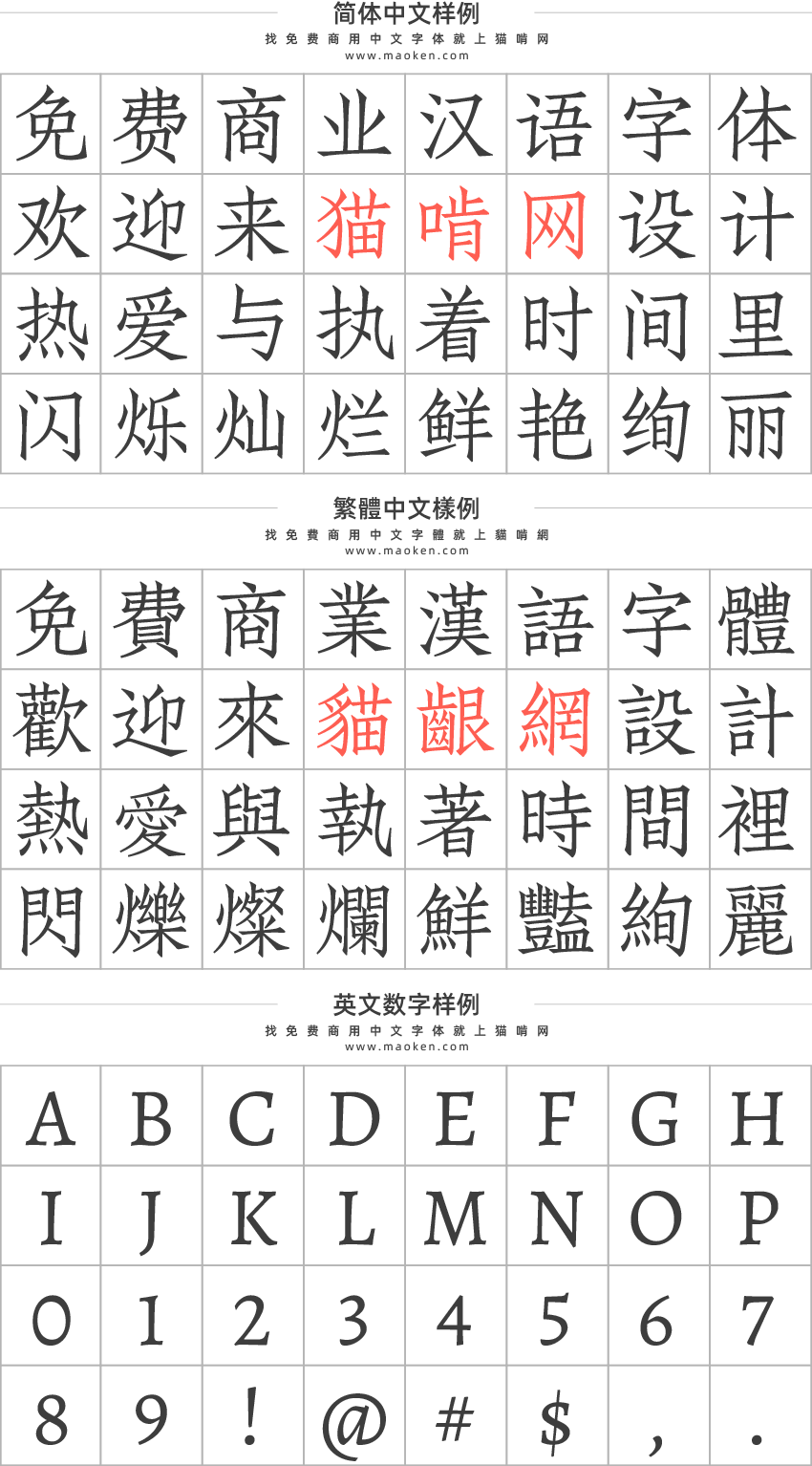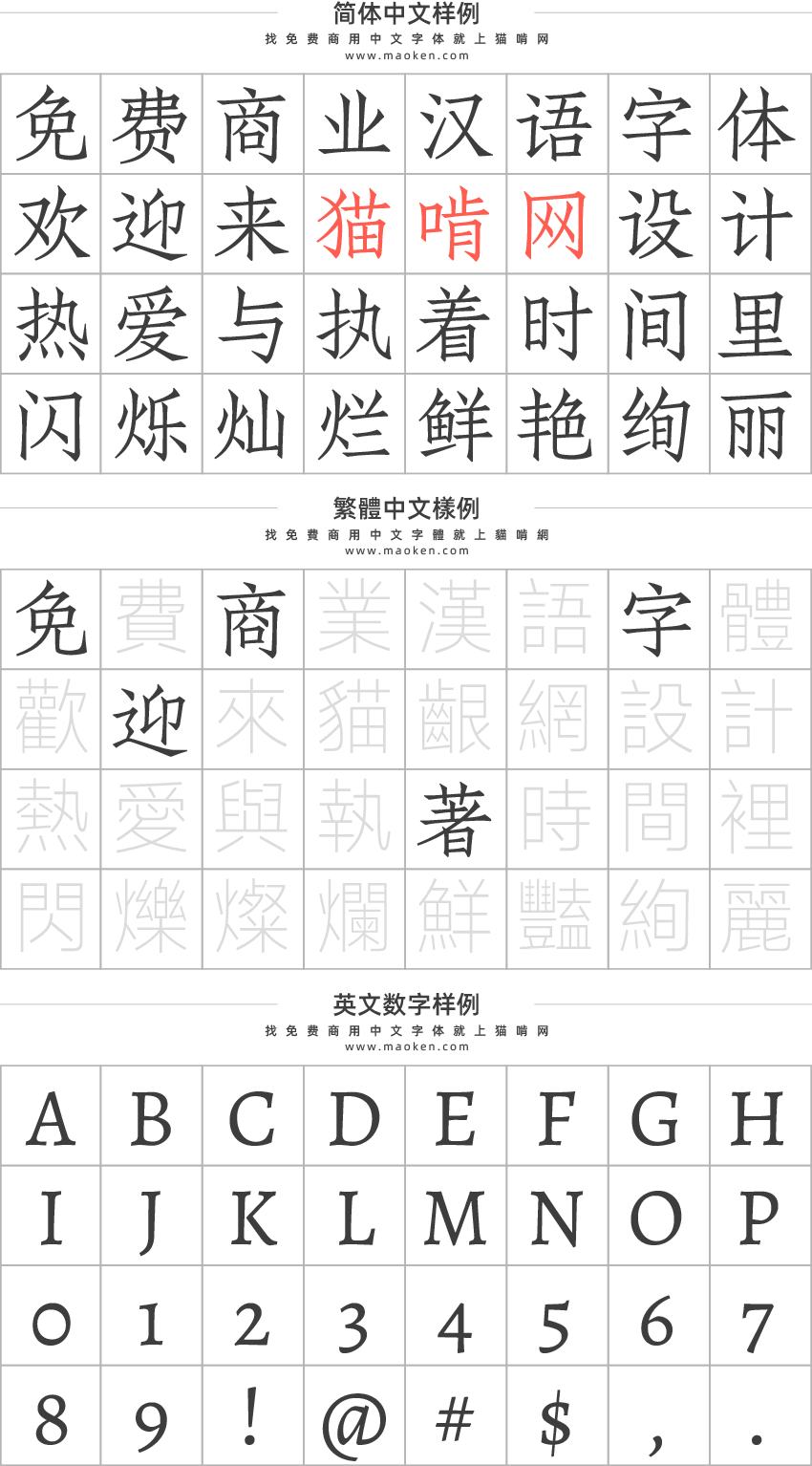
「朱雀仿宋」是璇玑造字的开源仿宋字体计划,志在最终提供高质量的、支持多语言的正文仿宋解决方案。
仿宋作为「宋黑仿楷」中文四大基础字体之一,长期缺乏开源许可证下的选择。我们希望「朱雀仿宋」可以弥补这一空缺,为开源软件与 TeX 社区贡献一份力。
上世纪初,仿宋活字一度品类繁盛,开发、应用风行一时。然而时过境迁,市面上的仿宋最终收敛于「华丰真宋」一系,这也是今天大多数人所熟悉的仿宋样貌。「朱雀仿宋」则以民国仿宋活字「南宋」为蓝本,在满足现代排印需求的前提下,尝试为正文仿宋字库带来一缕新鲜空气。
当前我们发布的「朱雀仿宋」仍为「预览测试版」,尚处于项目早期阶段;无论是设计风格还是字形、排版质量,都不代表正式版情况。因此,
「朱雀」的未来,由你定义
在开发「朱雀」的过程中,我们陷入了选择困难。于是,我们决定提早发布测试版,倾听「朱雀仿宋」的用户想要什么。我们真诚地邀请您拨冗填写此问卷:
璇玑正在尝试一种全新中文字库设计模式。得益于我们开发的最新技术,璇玑的设计师可以直接将人工智能作为设计工具去使用,我们也因此能以迭代的方式开发「朱雀」。
设计故事
智琮的智能造字技术可以让设计师将 AI 作为设计工具去使用,可快速从拼字甚至是手写字优化成高质量的风格字形。
开发一套开源仿宋字库的想法最早始于 2021 年初,是继「未来荧黑」项目之后,我们认为更有意义、也更具难度的挑战。随着设计研究的深入与技术进步,特别是去年以来 AIGC 技术的爆发,实现这一想法在今日遂成可能。
「朱雀仿宋」改刻自民国活字「南宋」,试图为这套沉睡数十年的字体赋予新生。「南宋」是 1932 年「百宋书局」推出的仿宋体活字,韩佑之设计原稿,邹根培雕刻字模。一经面世,即广泛用于书籍、期刊排印。「南宋」与大多数正文字体的设定不同的是,它中宫收紧,重心略靠右下,撇捺舒展,笔画的粗细变化强烈,含蓄秀美而充满力量感,在排印标题和正文时展现出浓厚的「书卷气」。
在「南宋」活字的基础上,「朱雀仿宋」稍稍削弱了笔画的对比度,适当地规整了字形结构与版面效果,同时最大程度地保留了「南宋」的独特气质与活字趣味。
「朱雀」是中国传统文化中「四象」之一,南方七宿之神。以「朱雀」为名,暗合了「南宋」渊源与「璇玑造字」的品牌名。
汉文正楷,什么时候可以安排一下吗?方正的虽好,但不能直接用。同样也是民国时期出的经典好字,对比各个楷体字,真的更有韵味和劲力。谢谢!
汉文正楷的四号复刻有汇文正楷,原版一号字形只在香港台湾的玻璃板照排时代有,而且还没数位化,原汁原味的一号数位复刻只有森泽的Smotoya Seikai,用异体字选择器调一下就能还原原版字形,缺点是字集只到pro,缺几百个常用字。而且汉文正楷的二号、三号、五号、六号、长体、疎体系列都没数位字体复刻,虽然汉文系列是楷体的鼻祖字体,但到今天楷体也没几个达到汉文水平
势力、力量 字体有点问题。看上去总感觉斜着的,我感觉是 力 字的问题。大家伙觉得呢?
字体很好看
少数屏幕和印刷品都很合适的仿宋,希望能出个TC版本(既原版民国南宋的字形)
南宋的旧字形,已经被特里王做出来了,叫做汇文仿宋,还挺不错的,但是此字体呢,是解决可以商用,并且给linux等开源操作系统的正文仿宋解决方案。
(原昵称为男性***)汇文仿宋是华丰不是南宋吧(
老王的文章只是提了一嘴汇文仿宋早期打算采取南宋,但样本太少难以实现,就把扫描档发给璇玑造字当参照了,因此诞生了朱雀仿宋,只不过朱雀为了通用性使用国标新字形,原版南宋的美感没有完全复现
我想给个建议,什么时候才能支持?“℃”,符号呢?
新版本好像支持繁体了,请您把图片更新一下
(原昵称:什么玩意?)最喜欢也是最常用的一款字体之一,有个“暐”缺失,不知道后续会不会补上。
摄氏度 —— ℃ 字体暂时不支持,能否增加?
现在使用的话,就是缺失很多标点符号,可以先补缺失的标点符号,成为新版本先使用着。
用来记笔记用,这个字体阅读不费力,省眼。不用去细看笔画,整个字形结构已进入了眼睛。目前版本使用缺点是英文部分,看着有点乱,笔画结构太复古。
英文同样省眼睛的字体是inter one mono.大小高地错落,不细看单个字母,映入眼睛是整个单词。英文部分可以考虑借鉴下。
字重加粗可以当显示字体了
好漂亮的仿宋!
非常漂亮的仿宋,期待朱雀推出新版本,能够完善繁简字库。
也期望猫啃推荐更多的仿宋字体。
看《三体》时候发现“淼”字没有,希望年底更新的时候考虑补上,谢谢了。
鄠邑区的鄠打不出来
这个字是《通用规范汉字表》三级字。
这个项目将来在做完新字形的版本后,是否打算做一个完全复刻「南宋」字形的版本呢?假如没有这个意愿,那是否愿意公开所搜集的原始字形资料呢?
有点像汉仪劲楷和方正北魏楷书,不过还是有差别。好看又免费,nice!
可使用范围不广
路过看看,没想到英文数字这么快就弄好了,特别喜欢这个字体,文雅又清晰,阅读不费劲
很多复刻老字体的,都会做的横向比较扁,显得臃肿。明明原来的字体就是偏瘦长的。
朱雀仿宋参考的「南宋」是呈正方形的,有横向开张的趋势。事实上在民国十余种方体仿宋中,只有唯一一款是瘦长的。如果您对字形有修改建议,欢迎在问卷中提出~
弥补了仿宋字体的空隙,伟大
实际使用仿宋的时候比较不多,除了红头文件用外场景很少,一般标题用黑体,内容用宋体,摘要用楷体
嗯 聊胜于无啊
工程制图还是会用到仿宋体的,不过那个是长仿宋体。这个字体如果可以拉长一下,宽高比调整为 3:2,或许在CAD 领域还有用武之地。另外,之前做一些 PPT 的时候,发现插图图题用黑体、图题下的解释说明用仿宋体其实也还可以(当然,每个人的审美不同,好不好看恐怕就是见仁见智了)。
仿宋的应用还是很广的,比如说用在一些文创产品、挂件摆件、古风设计上。现在比较流行的仿宋风格一是华丰真宋系(就是电脑上自带仿宋、方正仿宋这种风格),主要用在红头文件上,整体风格偏细;二是聚珍仿宋系,字形比华丰真宋系更清秀,但是目前没有开源或者免商的这类字体(除了Noto契丹小字仿宋)。作者能为开源社区贡献这么一款优质的仿宋字体,也是辛苦了,感谢作者团队
“之”字有点别扭 太立了,望大神改下
英文和符号 觉得用 STIX Two Text 这个更搭
Times风格字体搭配仿宋体效果不是很好
昨天已经有更新适配标点符号的版本了,猫啃上线了就来下载
仿宋字体大多笔画都偏细,有点影响阅读,这个刚刚好,很好看!美中不足是英文数字跟中文太不搭了。
因为这个字体目前还没有英文数字,个人推荐搭配Alegreya
简直是太棒了,终于能有一个可以用的宋体了。造福大家了。谢谢大大。
是仿宋,不是宋体
是仿宋啊 和宋体没关系~~~~~~~~~~~~~~~~~~~~~~~~~~~~~~~~~~~~~~~~~~
朱雀仿宋:这款字体的 走之 旁,是地地道道的 折弯 样式。比起其他几款由宋体拉长的 类似仿宋的替代字体(走之旁 就是直接一竖),更贴近中国风格。好字!非常看好、非常期待这款字体能更广而告之地,被大家和业界喜爱和广泛使用。团队用心了!
这是 OFL 字体,所以下载使用。
似乎还是首个国内开源仿宋字体呢……?
太棒了,太棒了
好字体,期待补全英文和和数字及符号